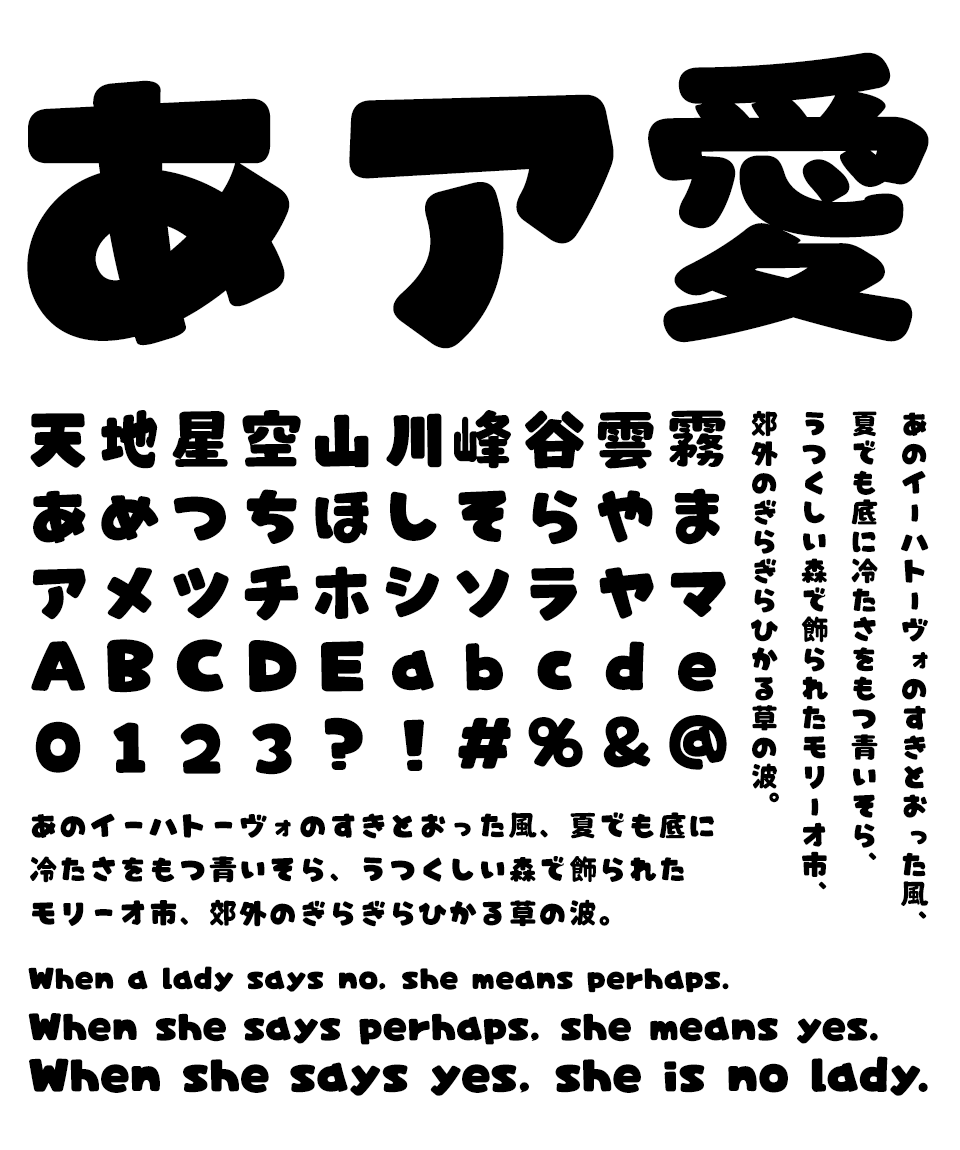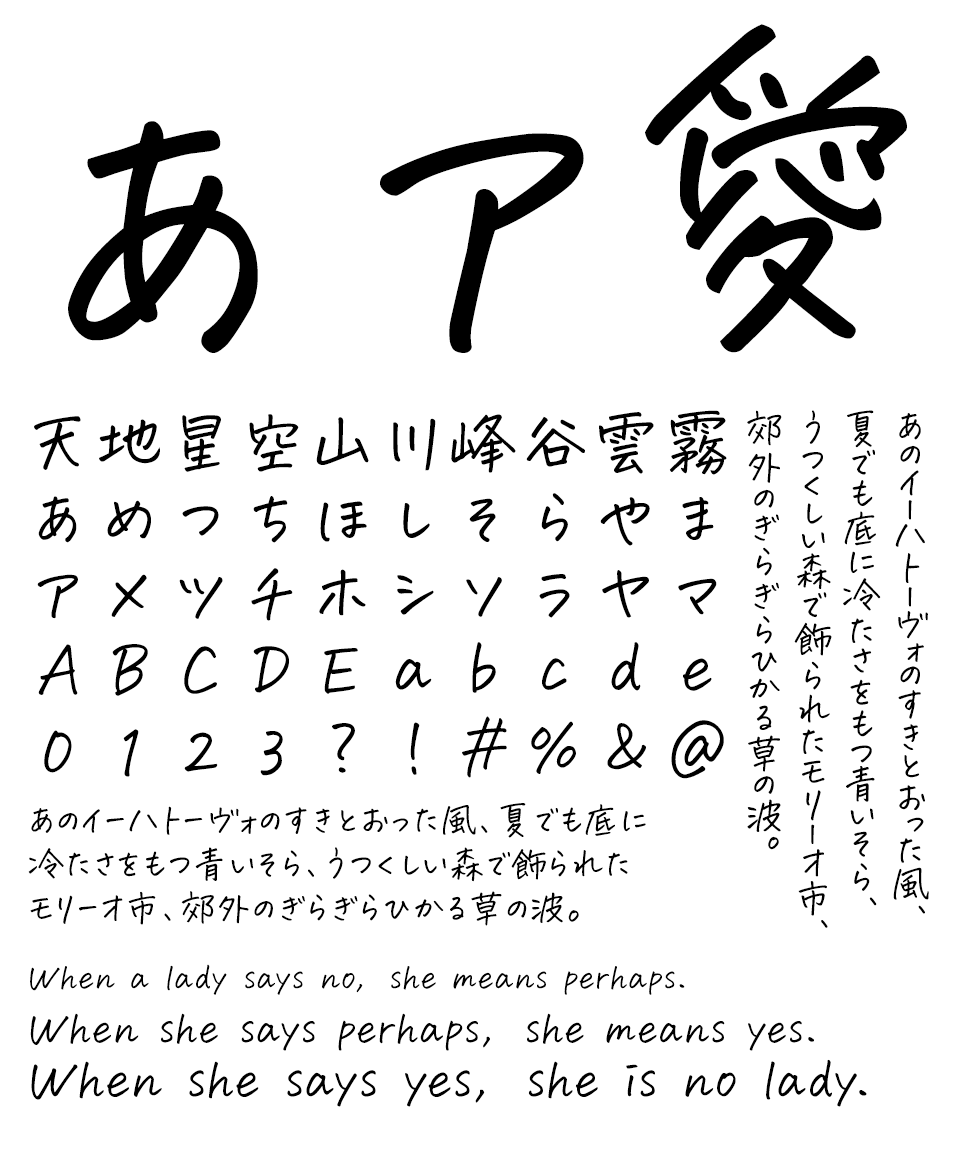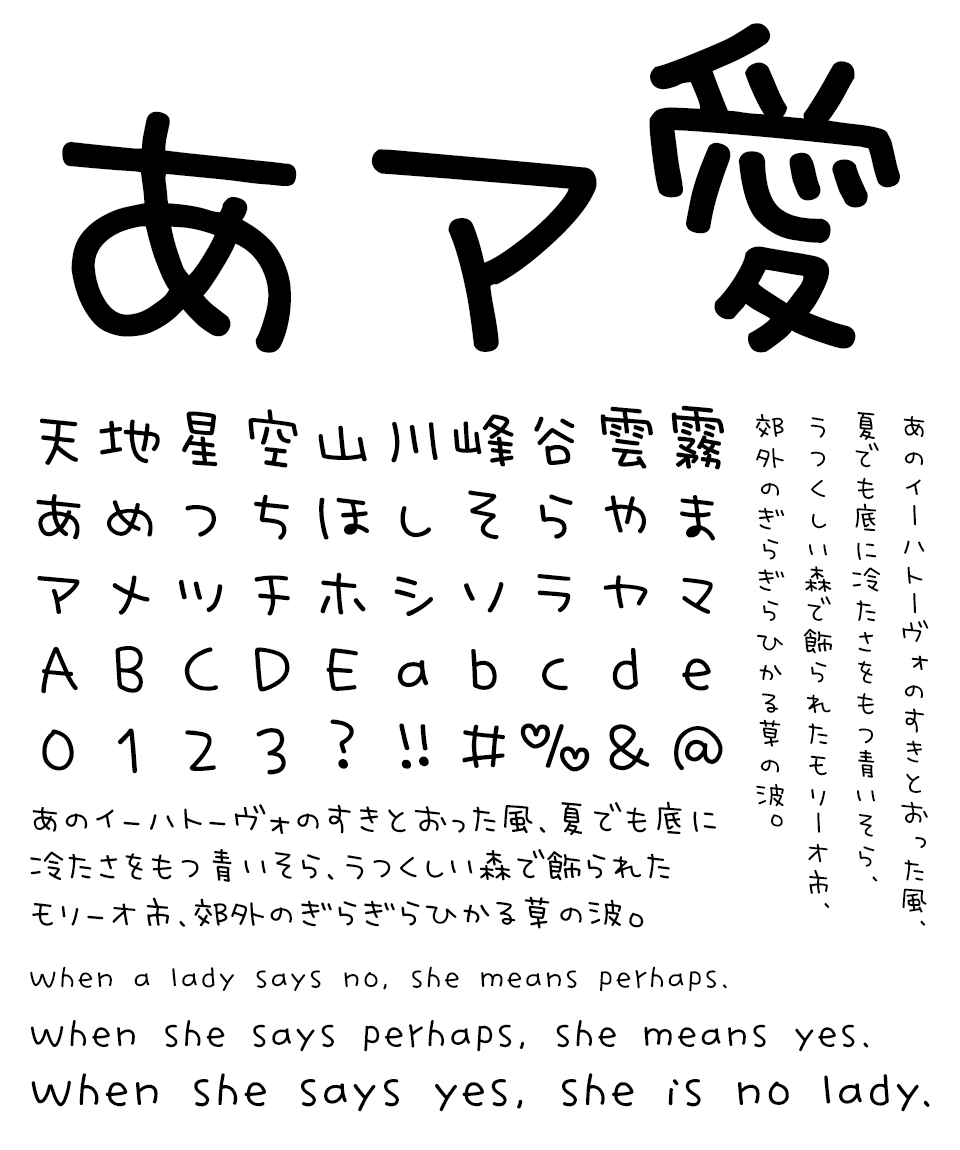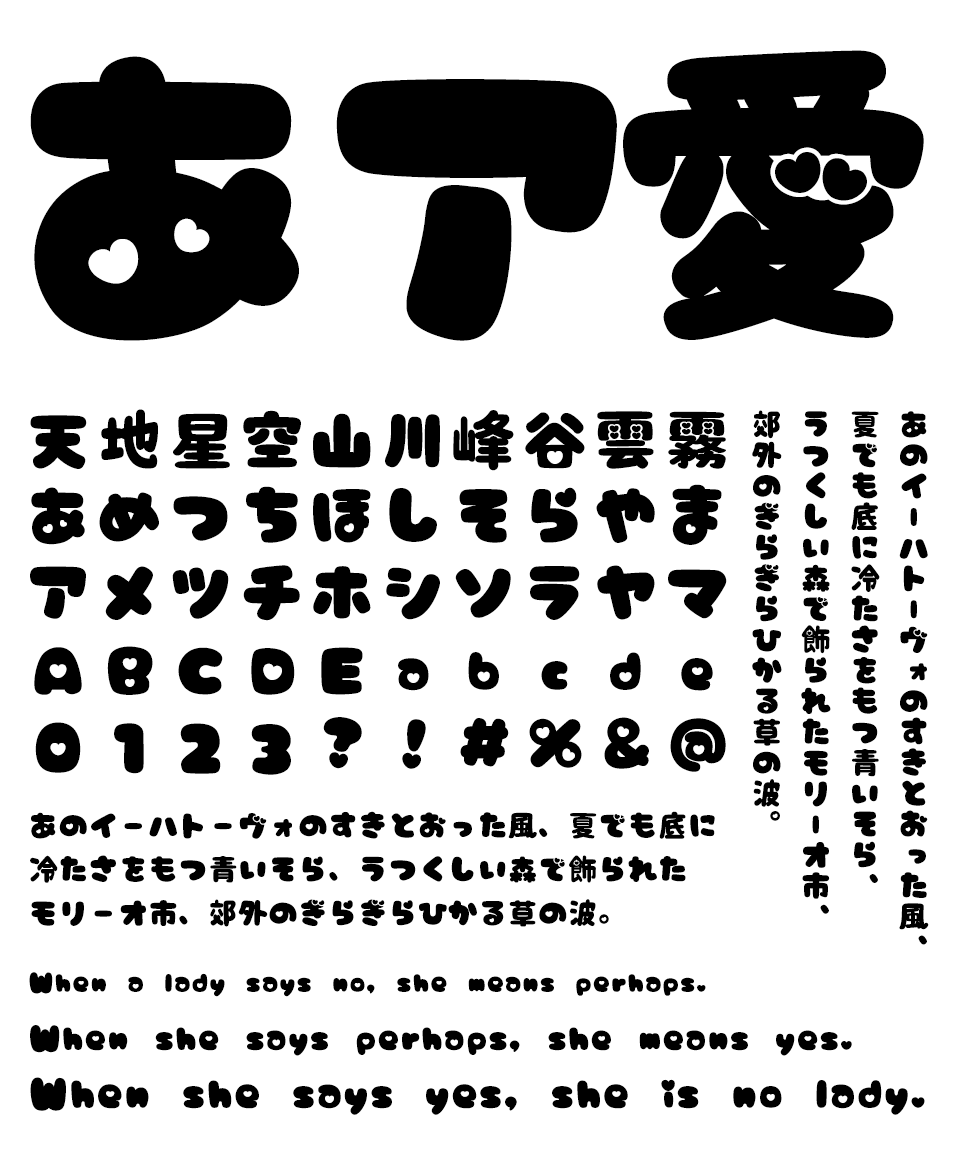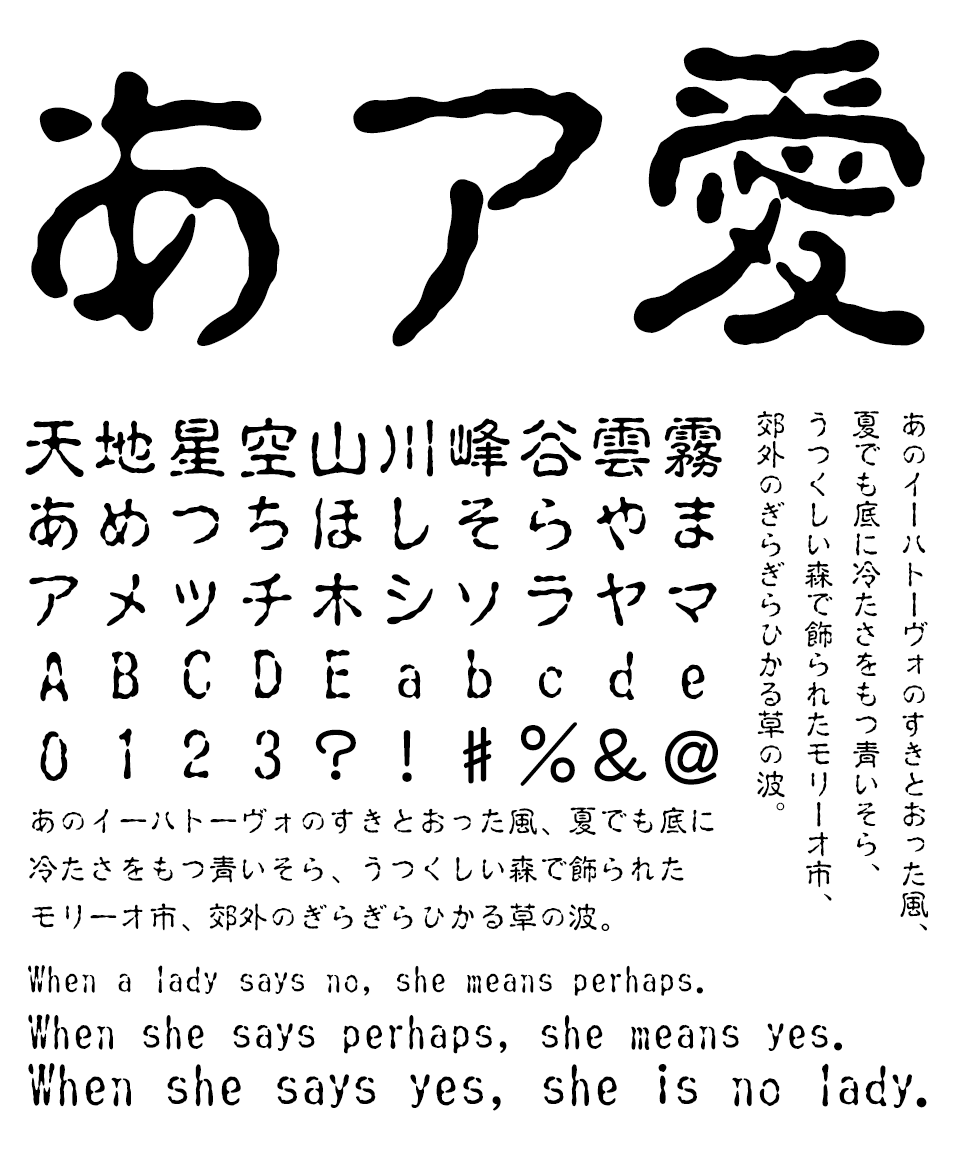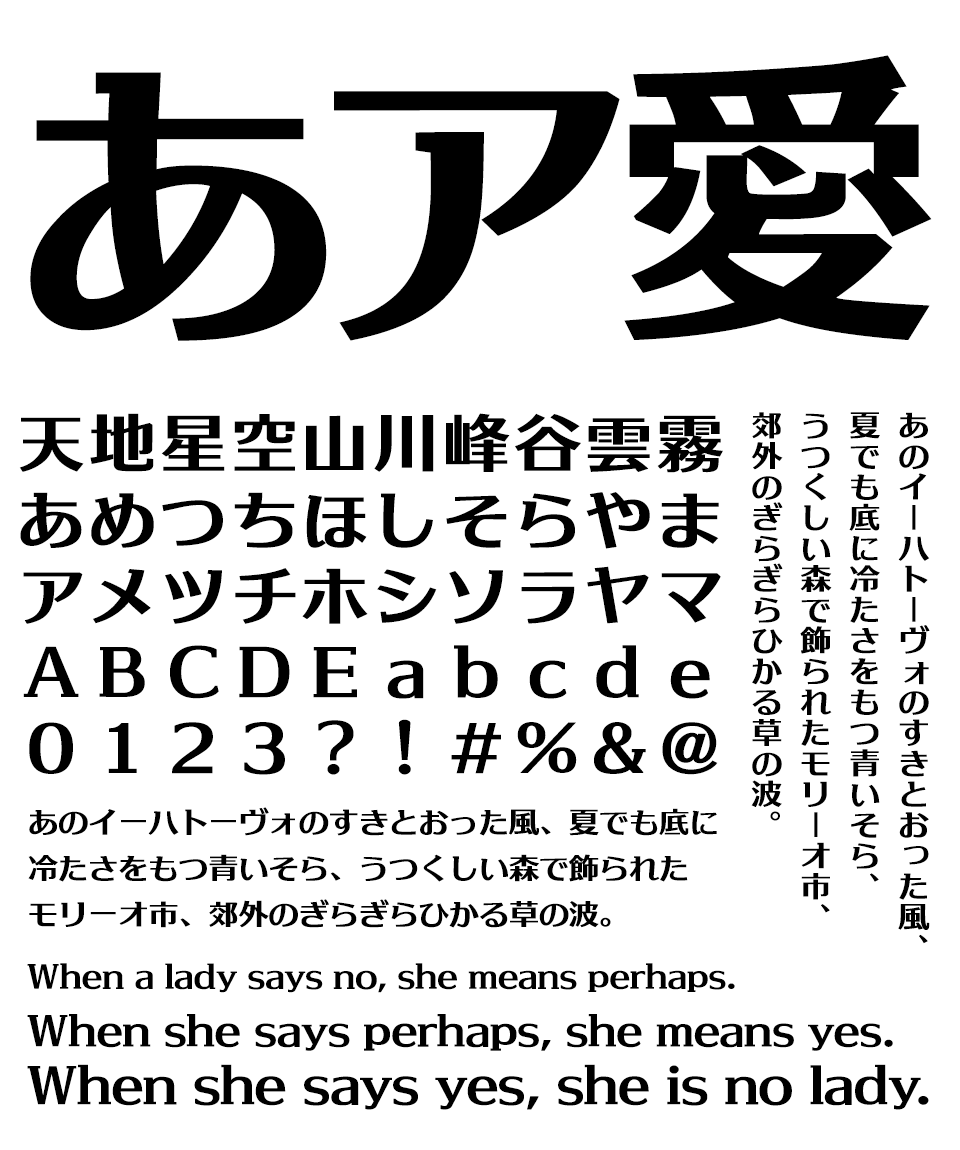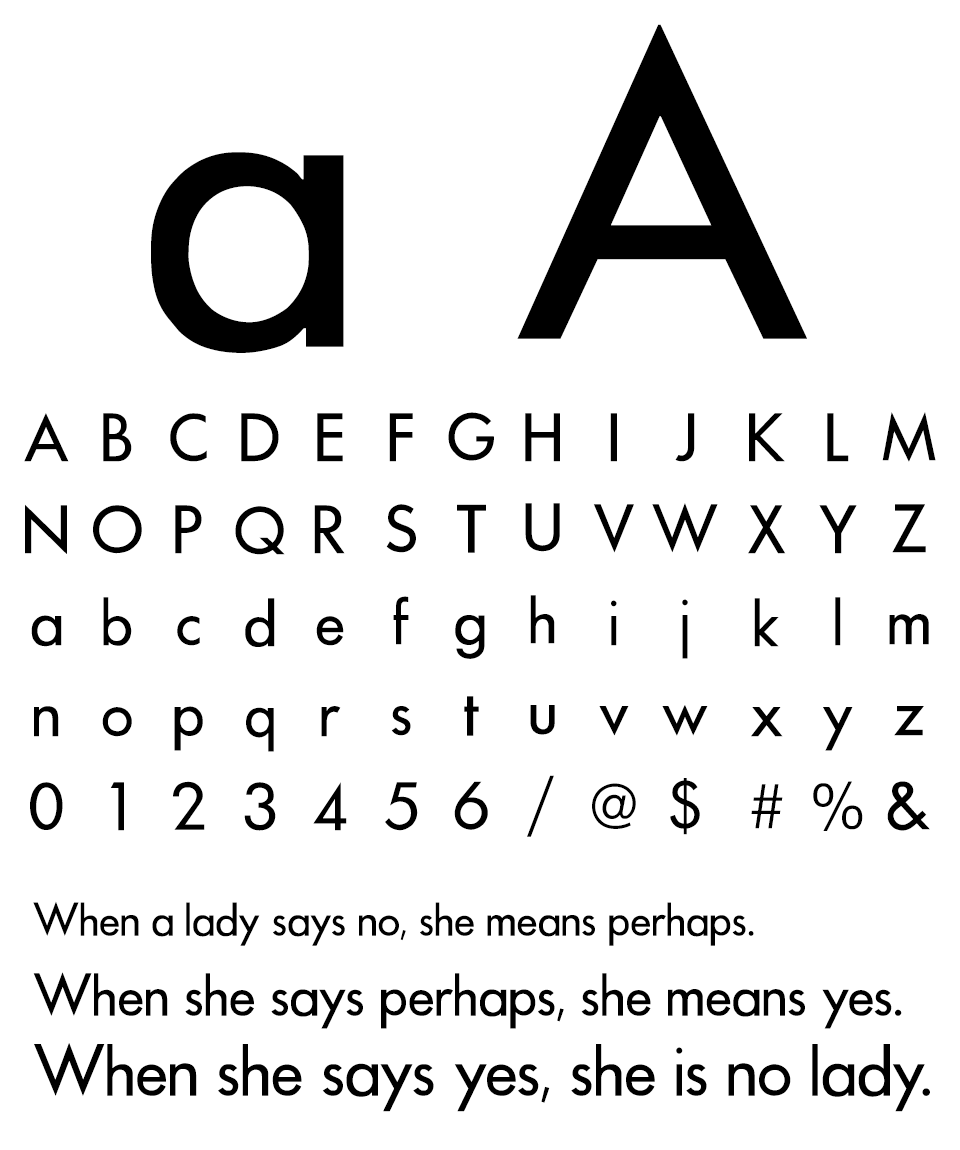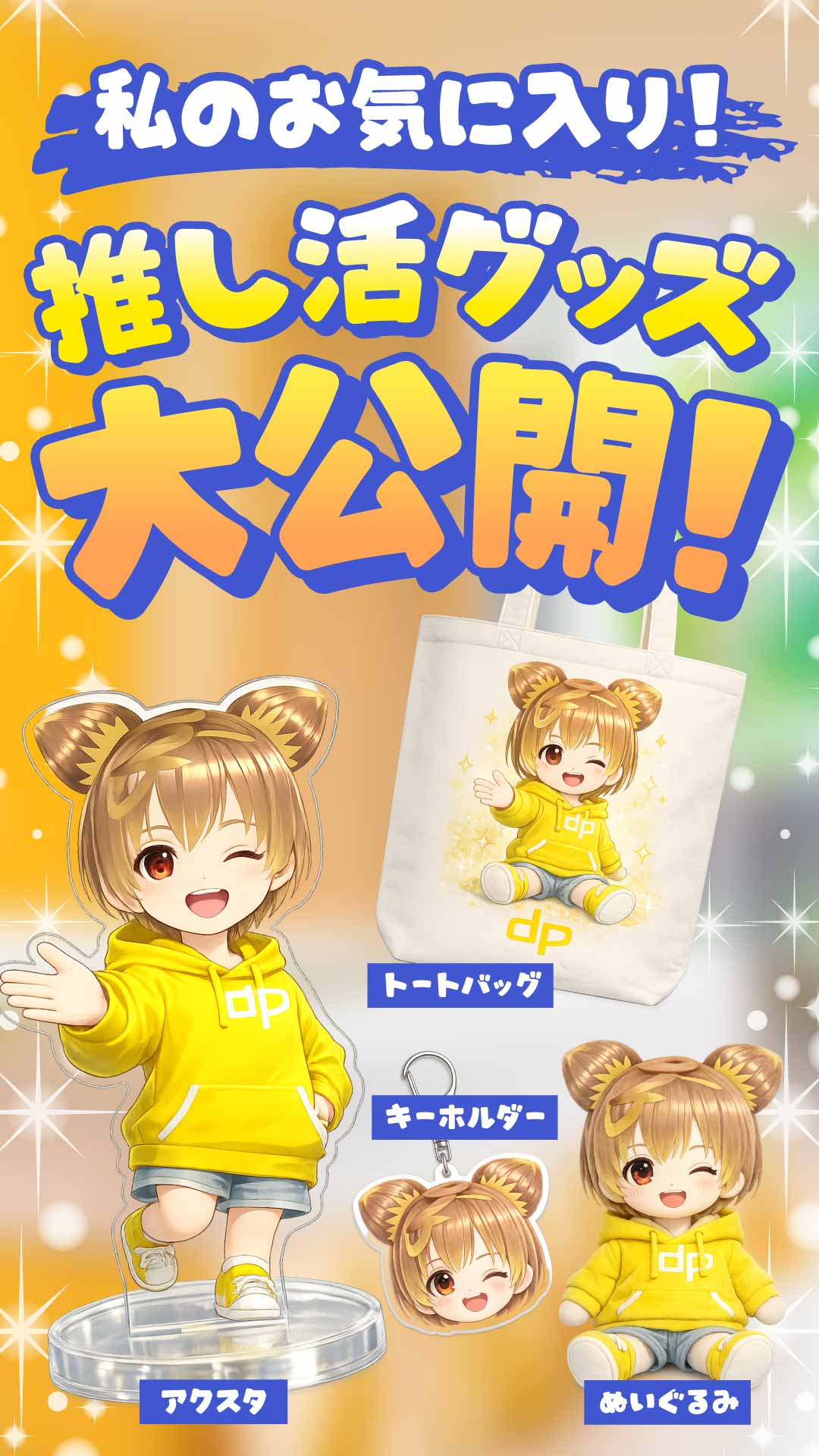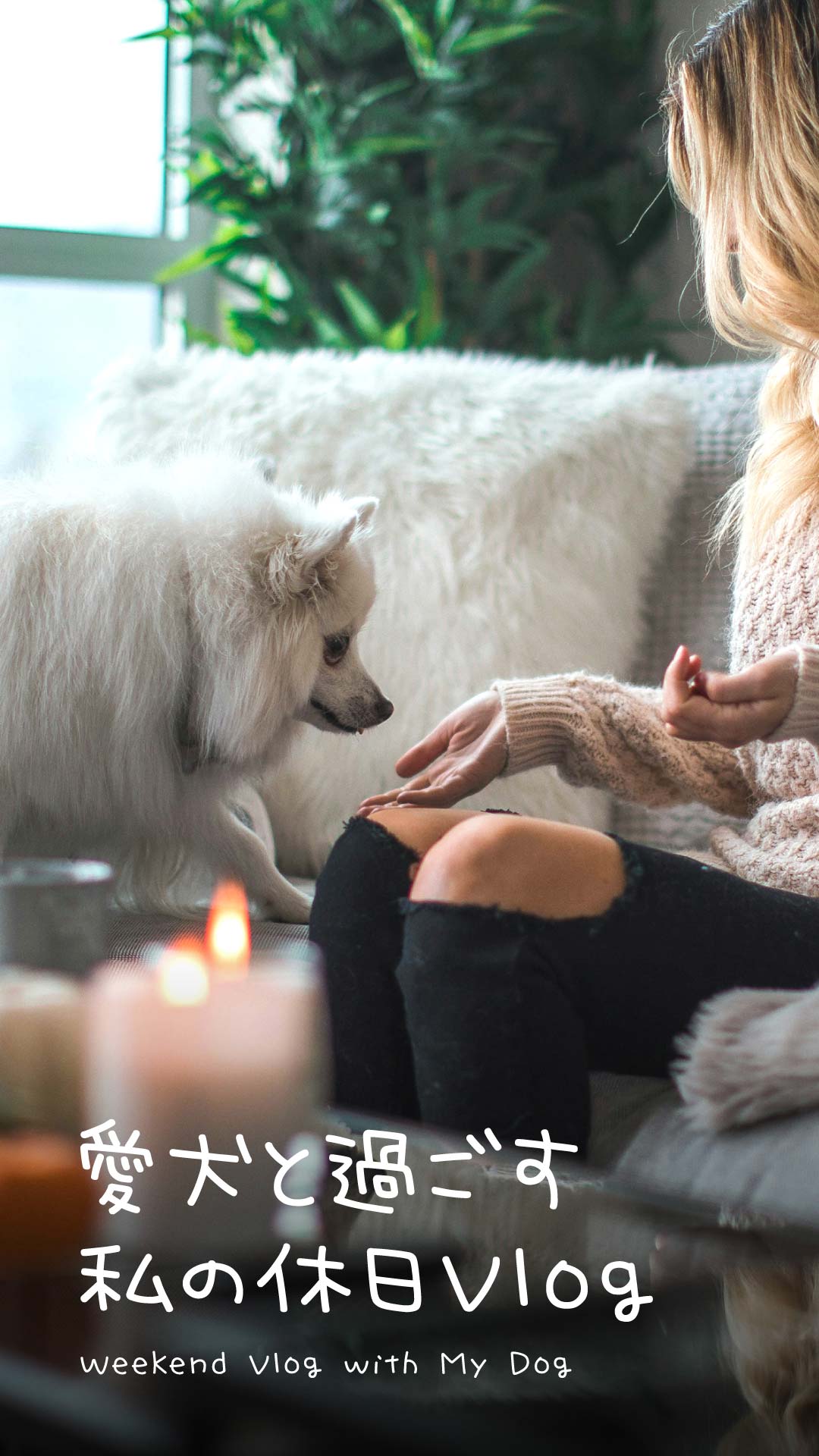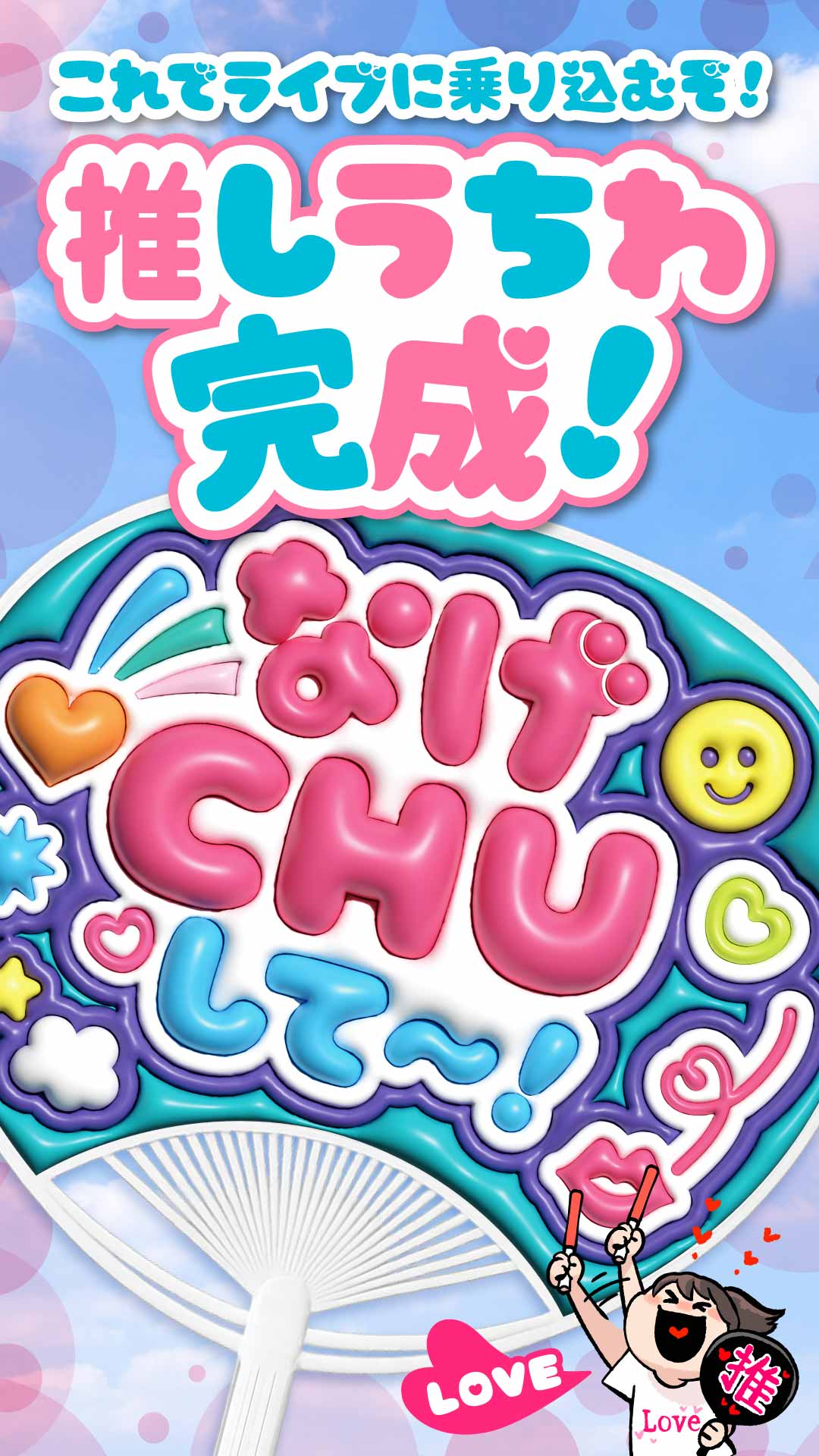
見られているのは「写真」だけじゃない。フォントが変わると、伝わり方が変わる。
動画が選ばれる理由は、編集スキルだけではありません。視聴者が最初に目にするのは「文字=フォント」。YouTuber・VTuberのサムネやテロップ、TikTok・ショートなどの縦型動画では、太さや丸み、可読性が再生数を左右します。本特集では、ジャンル別サムネ用書体から感情テロップ、推し活・Vlog・ビジネス動画向けまで、デザインポケットで購入できる商用利用OKフォントを厳選紹介。
縦型動画・ショート動画向けフォント
縦型動画は“最初の1秒で読める文字”が命。スマホで潰れにくい太め・丸み・高コントラスト設計の書体を軸に、Vlogの共感、推し活の熱量、ノウハウの信頼感、シネマの空気感まで、ジャンル別に「刺さる組み合わせ」を紹介します。
TikTok動画におすすめのフォント
かに沢のりおやんちゃポップrounded
スマホ画面でも瞬時に読める太さ・丸み・インパクトが重要です。短い時間で視聴者の目を引くため、ポップで元気な印象を持つフォントがよく使われます。
かに沢のりお
やんちゃポップrounded
元気いっぱいでやんちゃな子供をイメージしたポップな太めフォント。角丸デザインにより柔らかさもあり、強いインパクトと親しみやすさを両立しています。短いテロップでも視認性が高く、リアクション動画やエンタメ系TikTokと相性の良い書体です。
Instagram投稿・リールにおすすめのフォント
鈴木メモ花とちょうちょ
Instagramでは、投稿全体の世界観や雰囲気を作るフォントが好まれます。手書き風やナチュラルな文字など、写真の空気感を壊さずにアクセントになる書体が人気。
鈴木メモ
花とちょうちょ
ペンで書いた手書き文字をベースにしたフォント。右上がりの軽やかな筆跡とリアルな手書き感が特徴です。可愛らしい雰囲気を自然に演出できるため、インスタ投稿のテキストや写真のアクセントとして人気のある書体です。
雑談・日常Vlog動画におすすめのフォント
ゆるねこふぁくとりぃゆるねこ
雑談や日常Vlogでは、視聴者との距離を縮める親しみやすい手書きフォントがよく使われます。強すぎないデザインで、自然な雰囲気を作れる書体が向いています。
ゆるねこふぁくとりぃ
ゆるねこ
「ゆるねこ」は、ゆるく可愛い手書き風デザインが特徴のフォント。絵文字や吹き出しなどの素材も収録されており、動画編集やSNS投稿でも使いやすい構成になっています。柔らかい印象を与えるため、雑談動画や日常Vlogのテロップにぴったりです。
推し活・オタ活動画におすすめのフォント
かに沢のりおましゅまろポップ ハート
推し活やオタ活動画では、可愛さ・楽しさ・テンションの高さを表現できるフォントが人気です。太く丸みのあるポップ系フォントは、スマホでも読みやすく、動画の盛り上がりを視覚的に伝える効果があります。
かに沢のりお
ましゅまろポップ ハート
Z世代向け動画やライブレポ、開封動画に最適。縦書き対応なのでサムネ構成の自由度も高く、TikTokとの相性も抜群です。
ビジネス・節約術系動画におすすめのフォント
ビジネス解説や節約術の動画では、内容を正確に伝える読みやすさと、注意を引く強い見出しの両方が重要です。高い可読性で情報を整理できるゴシック体と、警告やポイントを強調できる個性的な書体を組み合わせることで、視聴者に伝わりやすいテロップ演出ができます。
イワタ書体イワタUDゴシックH表示用Pro
イワタ書体
イワタUDゴシックH表示用Pro
視覚特性に配慮して設計されたユニバーサルデザイン書体。輪郭がはっきりしておりスマホでも読みやすく、ビジネス解説や節約術などノウハウ動画のテロップに最適です。
アーフィックAR古印体B
アーフィック
AR古印体B
印影をイメージした個性的な書体。少しの緊張感や注意を促す雰囲気があり、「やってはいけない」「損する行動」など警告系テロップで視聴者の目を引きます。
海外風・シネマ系Vlogにおすすめのフォント
海外風Vlogやシネマ系動画では、ゴシックや欧文フォントを組み合わせた洗練されたデザインがよく使われます。日本語はシンプルに、英字は印象的に配置することで、映画タイトルのようなおしゃれな演出ができます。
フォントユーコムテロップ専用和文フォント AF-テロッププランタン
フォントユーコム
テロップ専用和文フォント AF-テロッププランタン
縦線を強調したテロップ向けの和文フォントで、動画字幕でも視認性が高い設計です。
フォントユーコムAFS復刻欧文フォント AFSFutuM
フォントユーコム
AFS復刻欧文フォント AFSFutuM
1924年にパウル・レンナーが設計したサンセリフ体を基にした欧文フォントで、すっきりとしたモダンな印象が特徴。
サムネイルで使いたいフォント (ジャンル別)
サムネは“内容の前に文字が読まれる”領域。ここでは配信ジャンル別に、背景が賑やかな画面でも埋もれにくい太さ・字面、クリックを誘う個性、初見が入りやすい雰囲気までを基準に選定。メイン1書体は使用例つきで、比較しやすいよう補助候補もあわせて紹介します。
ゲーム配信にオススメのフォント
ニィスフォントJTCじゃんけんU
クセが強すぎないのに個性はあるバランスで、背景がゴチャつくゲームサムネでも浮かずにまとまります。
ニィスフォント
JTCじゃんけんU
いろいろなところで活躍しているニィスフォントの人気書体の一つです。ほがらか、楽しい、自然、素朴なイメージです。
こちらもオススメ!ゲーム配信向けフォント
fontUcomAFSゴシック10■R
fontUcom
AFSゴシック10■R
レトロのゲームの雰囲気を醸し出すアウトラインフォント。外字と絵文字を100文字追加!!
FONT1000F1000-DON F2 Regular
FONT1000
F1000-DON F2 Regular
太く安定感のある書体です。縦・横のラインを中心に構成して安定感を強調しました。『ド~ンとした』イメージでデザインしたので、フォント名もDONとしました。
にっぽりライングリッチ ヘビー
にっぽり
ライングリッチ ヘビー
直線的な書体にグリッチエフェクトのかかった書体。
雑談配信にオススメのフォント
鈴木メモパンダベーカリー
角が丸くてやわらかい印象なので、初見でも入りやすい雰囲気に。ゆるいトーク・日常感のある配信タイトルと相性◎
鈴木メモ
パンダベーカリー
手描きのような自然なリズム感と、見出しやパッケージにも最適なしっかりとした太さ。そして何より手作り感のある可愛らしさ。手描き感が欲しいメニュー・メッセージカード・POP、インスタ映えする写真のアクセントに最適です。